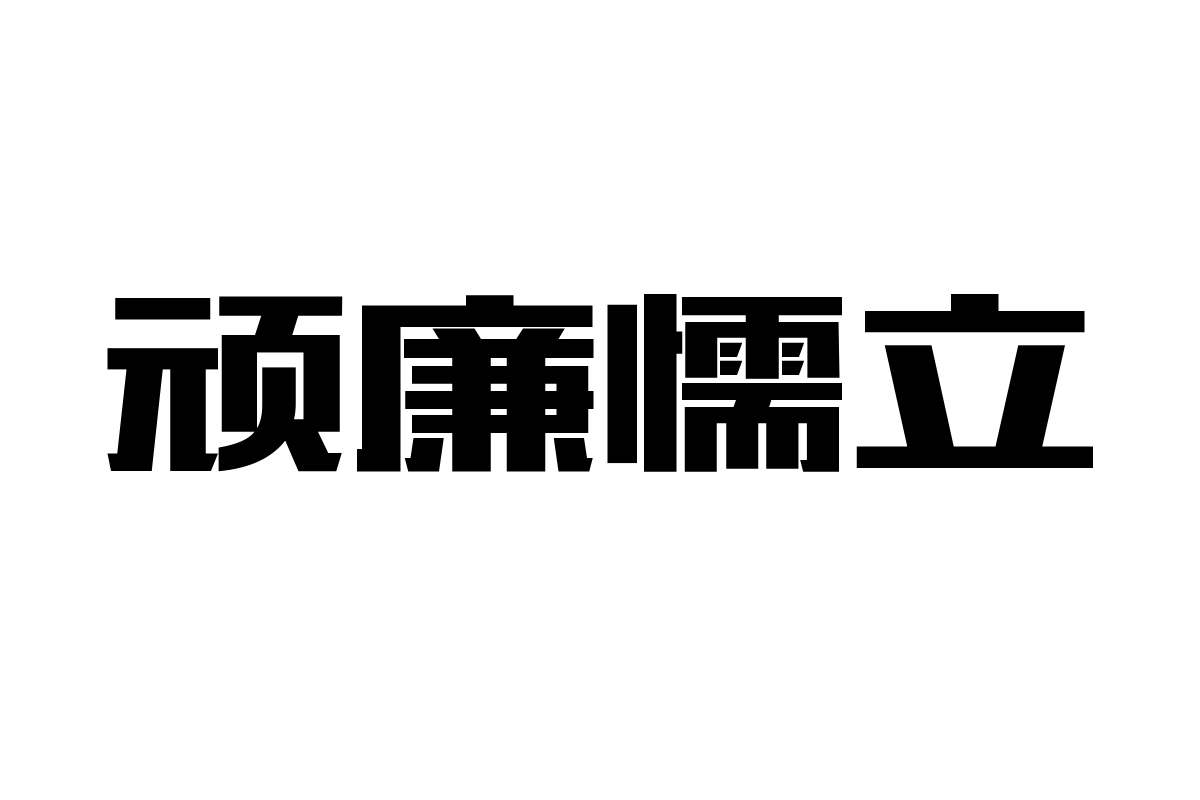
造字工房版黑体是一种基于传统黑体字形设计的现代字体,由造字工房团队精心打造。这款字体具有独特的风格和特点,适合用于各种设计场景,如标题、正文、广告等。
造字工房版黑体的字形结构简洁明了,笔画流畅自然,整体给人一种清晰、易读的感觉。同时,该字体也注重细节的处理,如字形的粗细变化、笔画的连接方式等,都经过精心设计,使得字体更加美观大方。
此外,造字工房版黑体还具有一定的可读性和适应性,适用于多种印刷媒介,如报纸、杂志、书籍、广告等。它的设计风格独特,既有传统黑体的特点,又不失现代感,能够很好地融入各种设计元素中。
总的来说,造字工房版黑体是一款非常实用的现代字体,无论是用于商业设计还是个人创作,都能展现出其独特的魅力和价值。